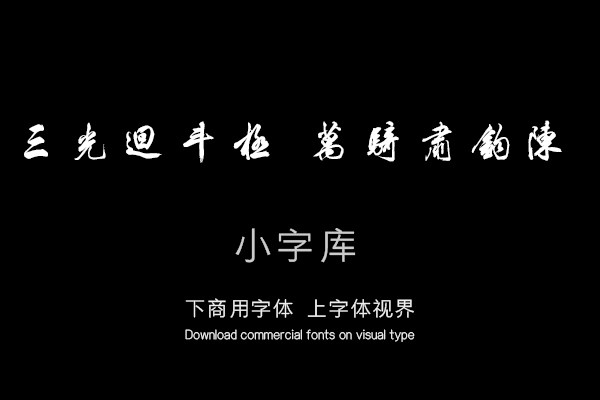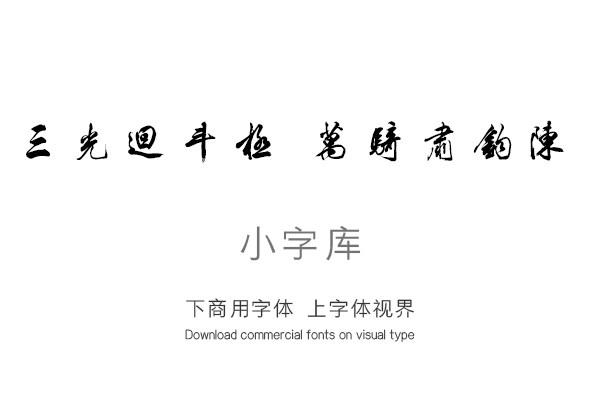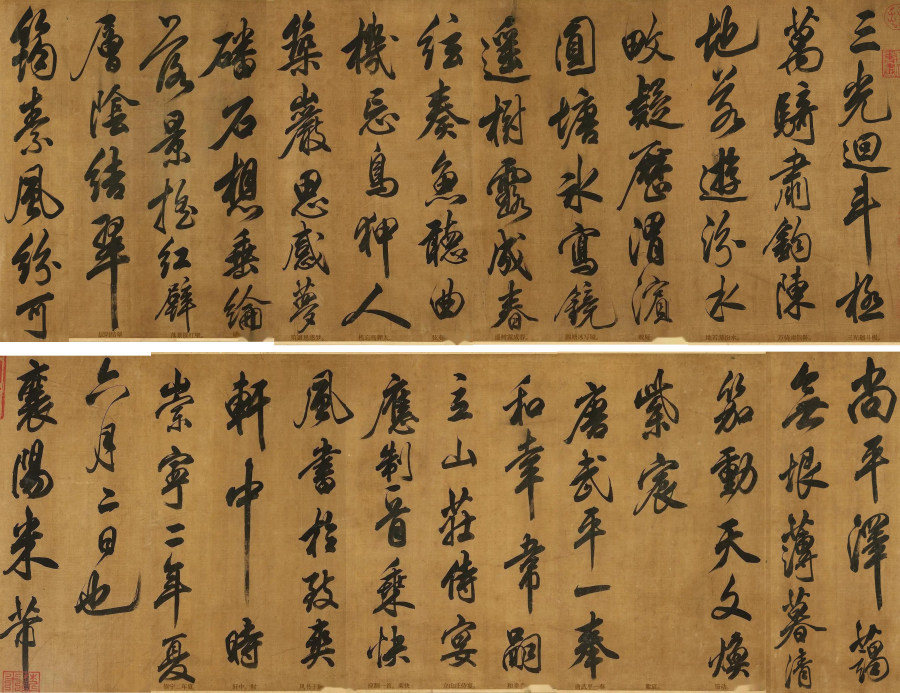
汉标米芾唐诗五律一首
《汉标米芾唐诗五律一首》是一款根据北宋米芾唐诗五律一首,经过再次调整制作的小字库,该小字库共收录了该真迹作品中约139个字体。
三光回斗极,万骑肃钩陈。地若游汾水,畋疑历渭滨。圆塘冰写镜,遥树露成春。弦奏鱼听曲,机忘鸟狎人。筑岩思感梦,磻石想垂纶。落景摇红壁,层阴结翠筠,素风纷可尚,平泽蔼无垠,薄暮清笳动,天文焕紫宸。唐武平一奉和幸常嗣立山庄侍宴应制一首乘快风书于致爽轩中时。崇宁二年夏六月二日也 襄阳米芾